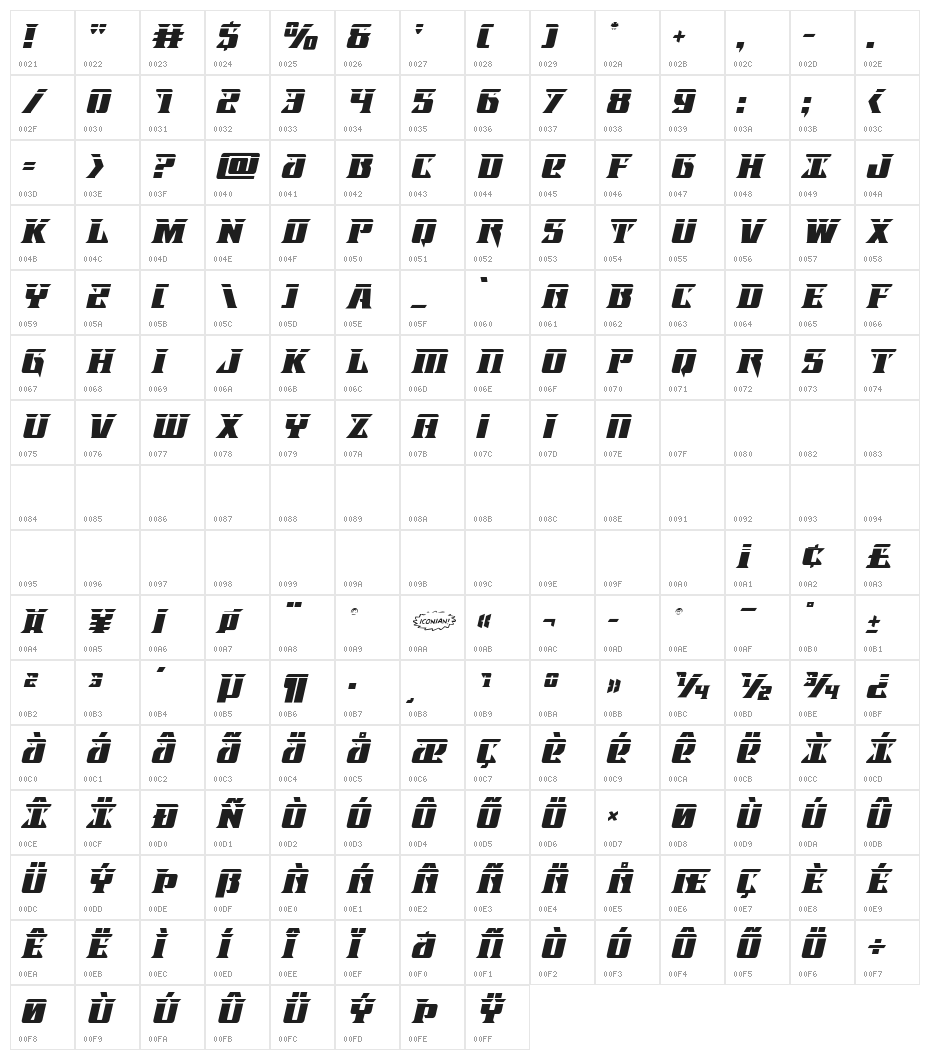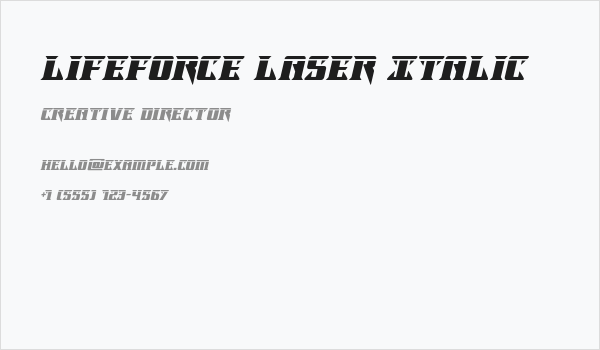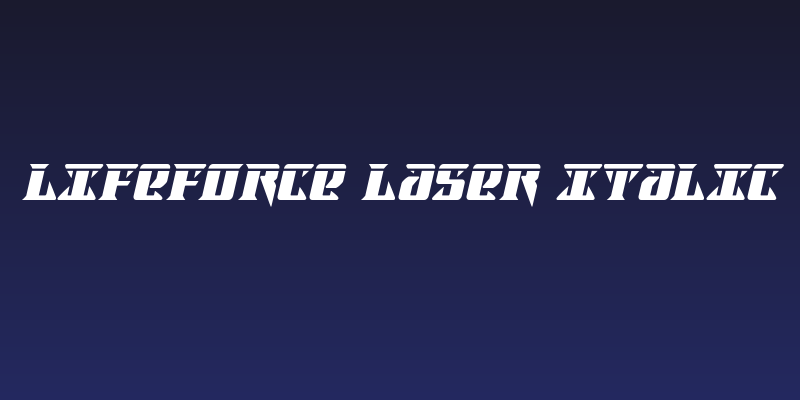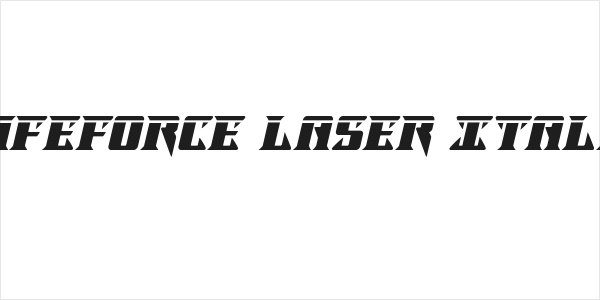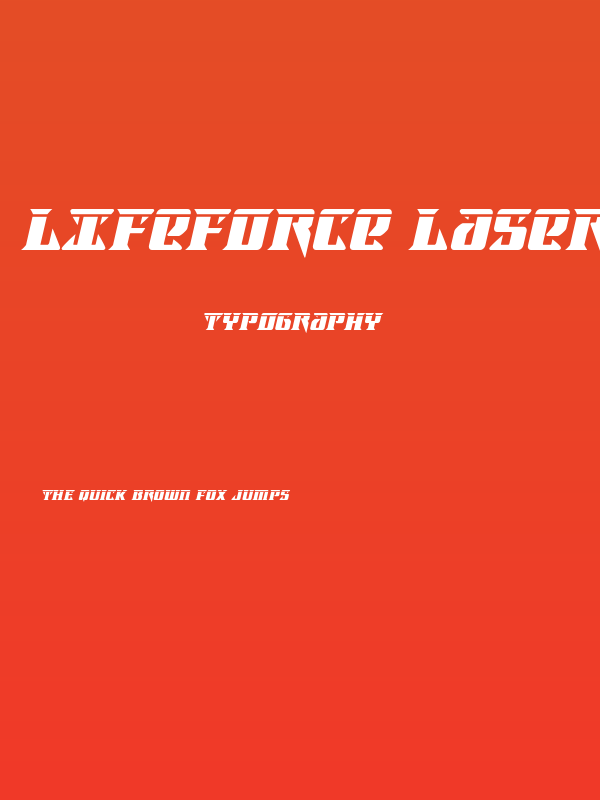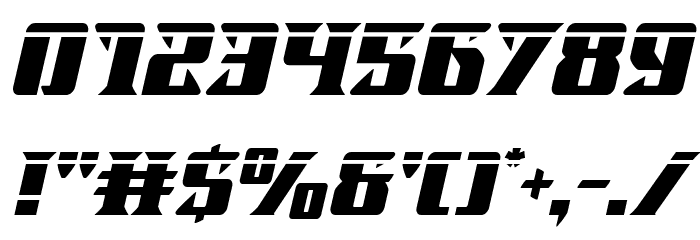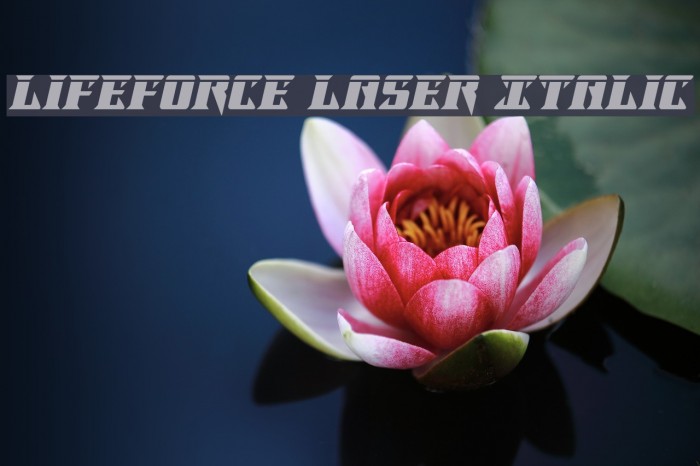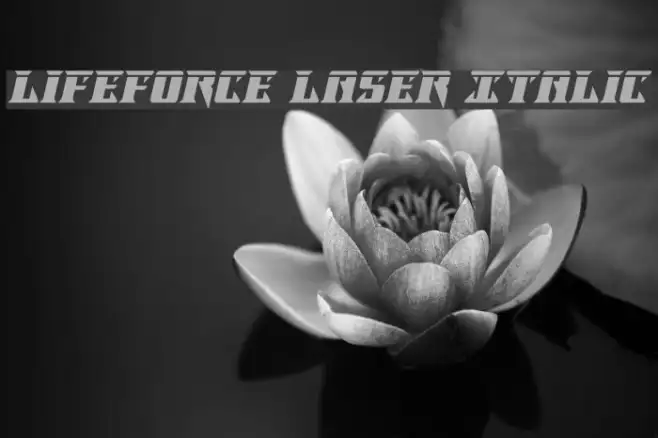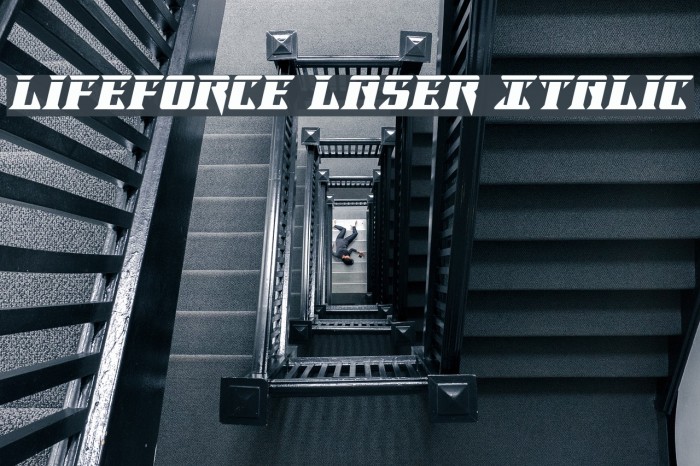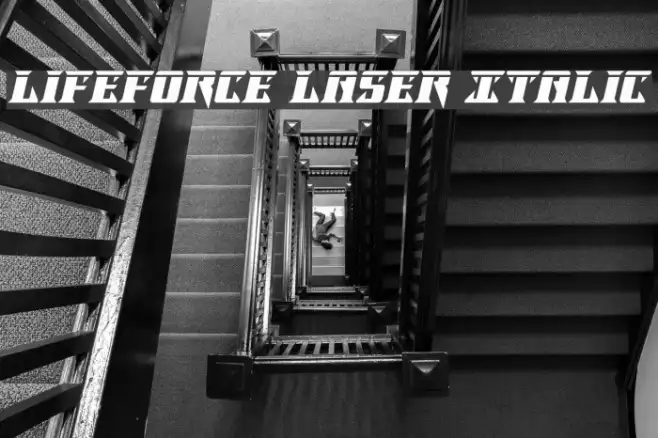
Lifeforce Laser Italic Font
| Proyectos propuestos | Ideal for sci-fi themed projects, video game titles, movie posters, and branding that requires a modern, edgy look. |